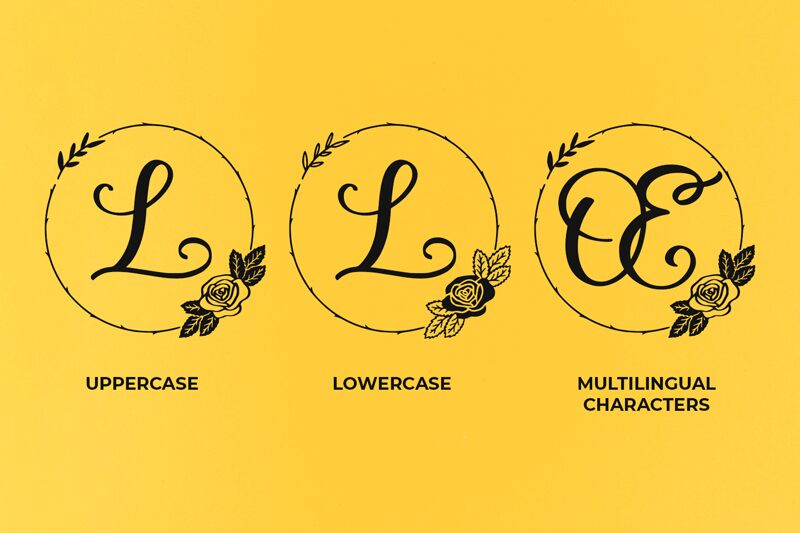
Rosegram
Rosegram, créée par Abo Daniel Studio, est une police d'affichage décorative de type monogramme, où les initiales en écriture manuscrite fluide sont encadrées par un fin cercle dessiné à la main. Chaque caractère est accompagné d'un discret motif de rose et de feuilles, conférant à l'ensemble un aspect floral gravé, sans surcharge ornementale.
Rosegram est idéale pour les faire-part de mariage, les logos, la papeterie, le packaging de boutiques et les visuels pour réseaux sociaux nécessitant un cadre élégant. Cette police gratuite transforme chaque lettre en un véritable emblème ou une étiquette prête à l'emploi, bien au-delà du simple texte.